文字是表达语言的一种符号,而字体作为文字的外在表现形式,在平面设计中它是必不可少的元素,本文以字体设计为研究对象,阐述了字体设计的重要性,探讨了字体设计在商品包装设计,标志设计,封面设计及平面广告等平面设计作品中的应用,以供平面设计人员参考。话不多说,我们直接上图。
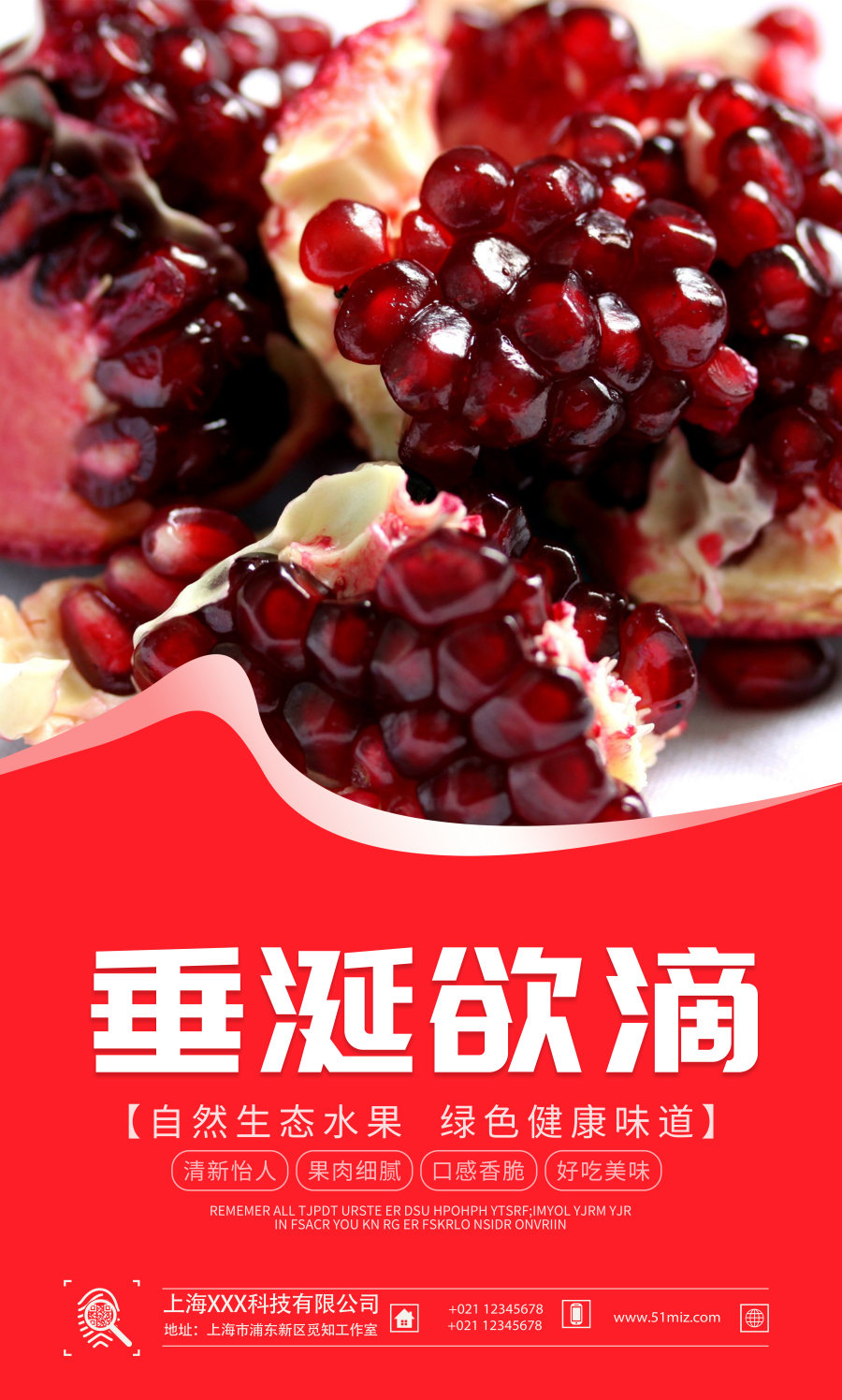
粗壮有力的黑体是被广泛使用的基本字体,不管是手机端还是电脑端基本上都是主流的屏显字体。 这款印品招牌体 中黑,相比于传统的黑体,更加圆润,让人感觉更加舒适。黑体字笔划整齐划一,它浑厚有力,朴素大方并且引人注目。 设计师在设计、做字过程中,做了一些细节调整优化。它的弯钩都作了一点线条处理,看起来不那么死板。它的一撇一捺像极了柳絮飘飘。这款字主要笔画粗壮,带有纤细笔触,字形紧聚,但不失美感。 设计师希望这款字体能被更多的人喜欢和使用。
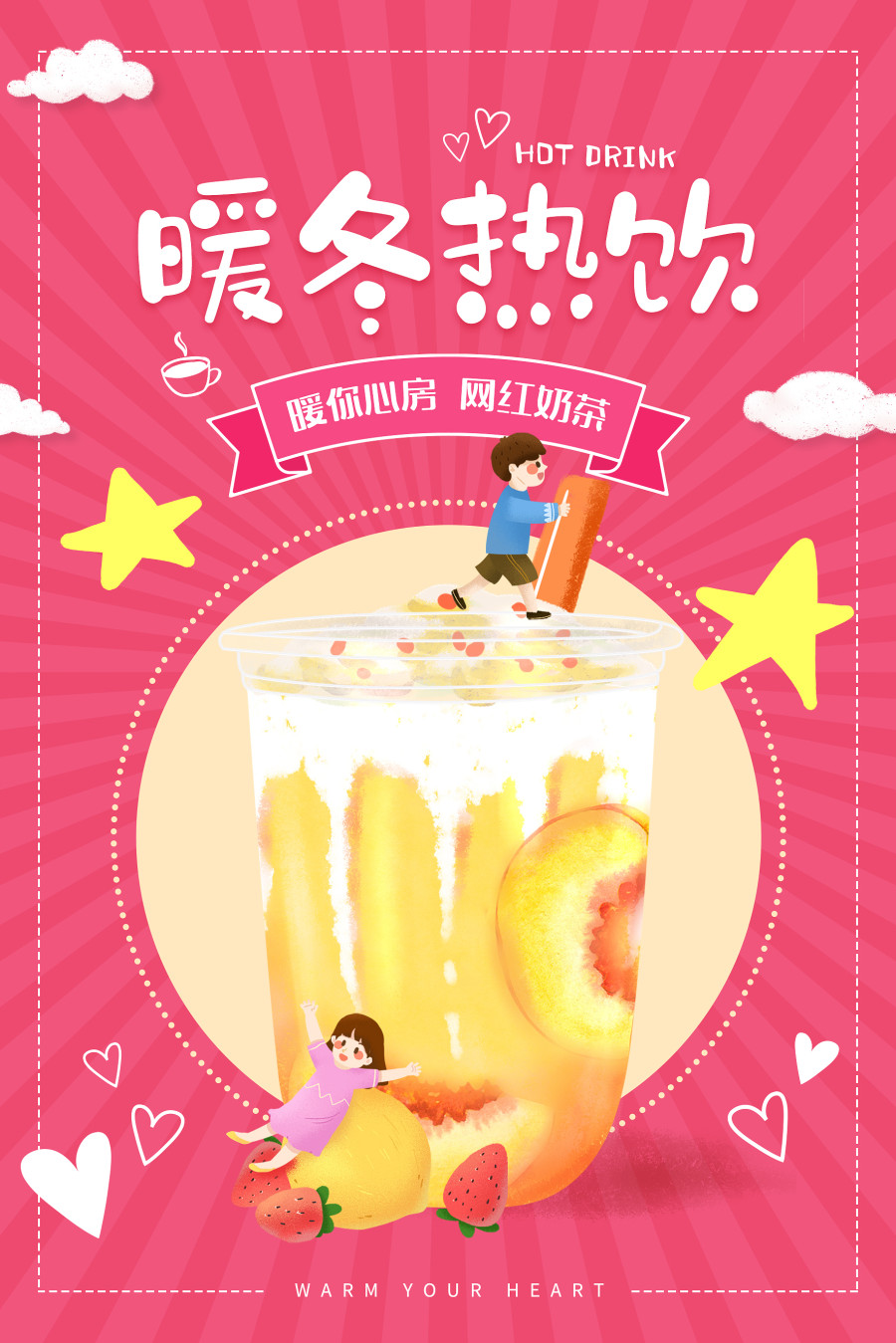
上首叮当体,字体风格方正,字体笔画竖勾、竖折都做了简化的处理。字库整体特征坚硬、有力,具有现代、国际化的指向性,适用于搭配标志、广告标语、商业广告等高端属性。
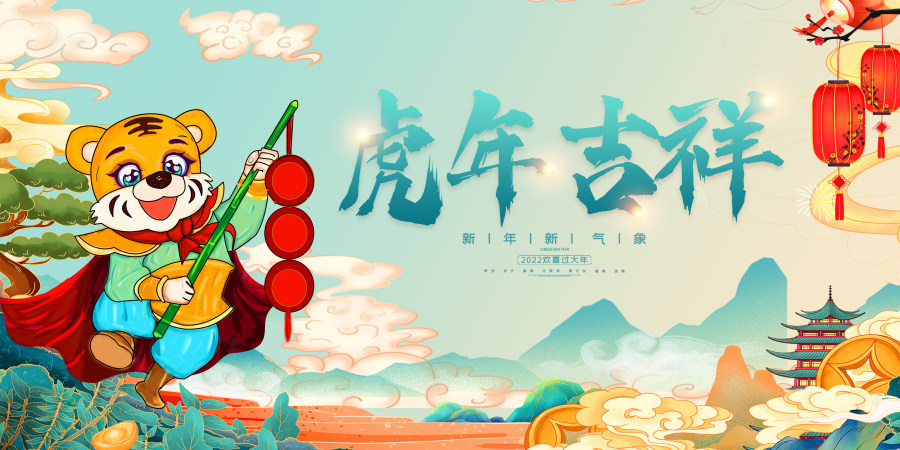
上首疾风书法体,字体风格锐利,钝点强力,夸张的笔锋增添了字体的活跃性,而且字体中粗细衔接,使字体显得生动。